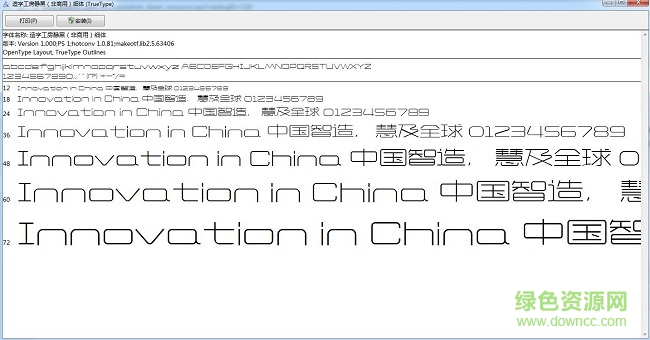
造字工房靜黑細(xì)體是一款線條纖細(xì)的黑體字體,該字體筆畫轉(zhuǎn)折處理精巧,柔中帶剛,清新大氣,工整而不失韌勁,可以用作文字標(biāo)題或廣告字體,喜歡的小伙伴快來下載吧!
細(xì)線構(gòu)成的字體,容易使人聯(lián)想到香水、化妝品之類的產(chǎn)品!
黑體會(huì)比宋體更容易給人帶來較為強(qiáng)烈的印象,因此黑體字的直觀效果相對(duì)于宋體等手寫體來說要更強(qiáng)一些。